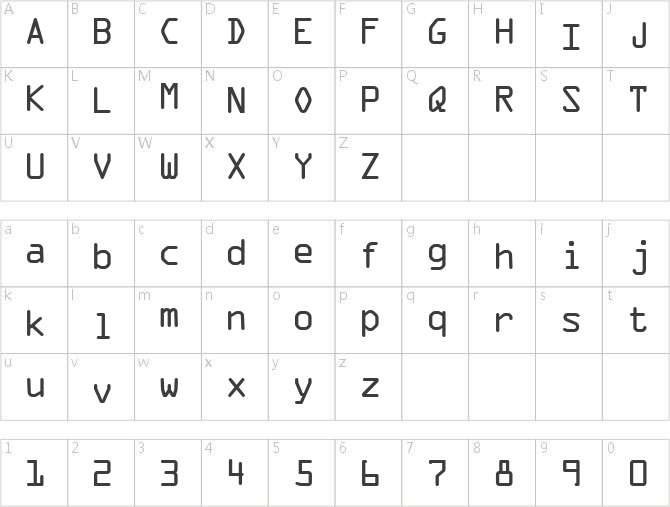
OCRAExtended字體當(dāng)前操作系統(tǒng)缺少ocr a extended字庫(kù)是一款讓人賞心悅目、百看不厭的英文字體,適合各類廣告和產(chǎn)品包裝設(shè)計(jì)應(yīng)用,字體大小0.05MB,格式為ttf字體,上傳用戶是shiqiuping,作者/版權(quán)方為未知